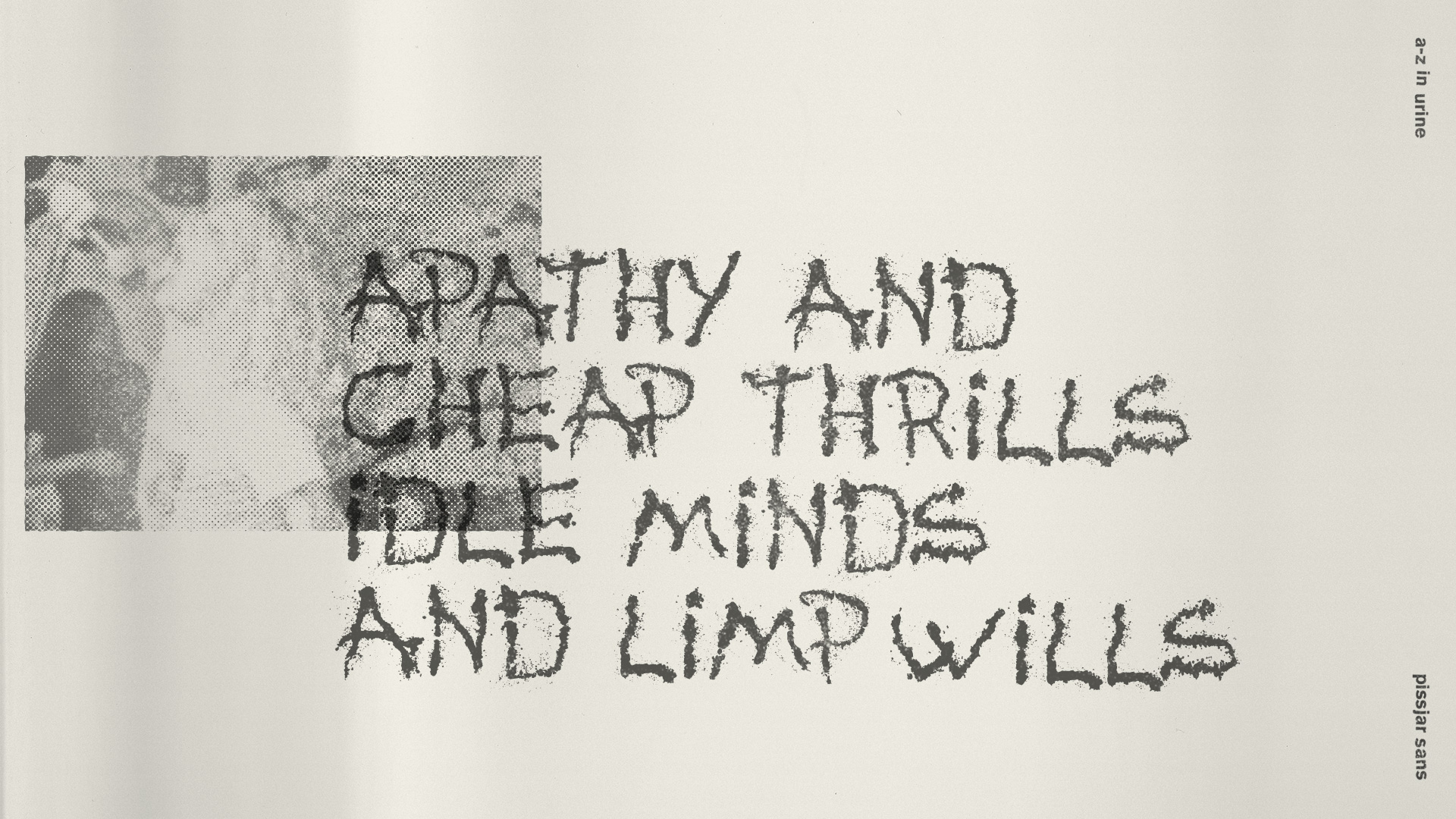
Pissjar Font
Pissjar Font est une police entièrement composée d’urine. Il a été réalisé par le groupe punk suédois Pissjar. À l’origine, ils avaient l’intention de l’utiliser comme image pour la pochette de leur prochain album, Apathy & Cheap thrills, mais ont ensuite décidé de l’étendre et de créer un alphabet complet et une police téléchargeable.
Ils ont pissé à tour de rôle sur des draps étirés pendant 6 mois, ont créé les lettres individuelles, les ont vectorisées, puis éditées avec un logiciel de polices. Le résultat s’est révélé étonnant, comme ils l’ont nommé. Merci à Pissjar Band pour la création et le partage de cette police.